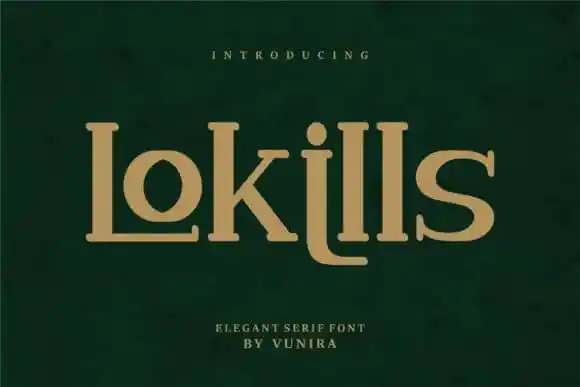
A Lokills Serif Font é uma fonte serif que oferece letras maiúsculas, ligaduras e caracteres multilíngues completos. Esta fonte não apenas se destaca por sua elegância clássica como também por seu charme refinado. Suas letras são arranjadas de maneira neat e bela, o que a torna uma opção perfeita tanto para projetos formais quanto para designs informais. Ideal para quem valoriza a simbiose entre modernidade e tradicionalismo, essa fonte está fadada a se destacar em qualquer projeto. Composta por letras impecavelmente organizadas, ela oferece um toque de elegância que se torna perfeitamente harmonioso em diversos estilos gráficos. A Lokills Serif é uma escolha inteligente para aqueles que buscam transmitir elegância e sofisticação através dos seus designs, seja na criação de materiais informativos ou visuais promocionais.